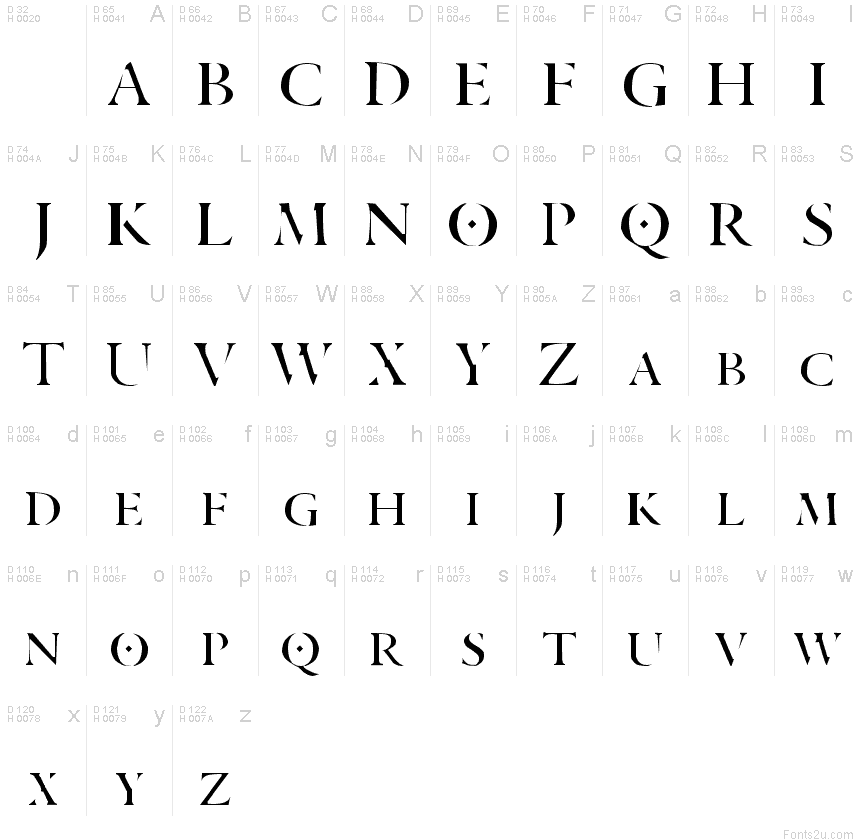
Aranea من rzy/SDFonts هو خط مزخرف بزوائد (serif) يضفي طابعاً مظلماً ومسرحياً. حروفه طويلة وأنيقة تنتهي برؤوس حادة كالإبر، وكأن ضربات القلم قد رُسمت بريشة حادة على ورق نقي. التباعد يبدو متقارباً ومقصوداً، مما يمنح الكلمات توتراً منسوجاً يشبه خيوط العنكبوت، وهو أمر يناسب كل ما هو غامض أو سحري أو خطر بعض الشيء.
باستخدام Aranea، تكتسب العناوين على الفور دراما قوطية أشبه بالقصص الخيالية يصعب تجاهلها. يتألق هذا الخط المجاني على أغلفة كتب الفانتازيا، ومجلات العالم الخفي (zines)، وشعارات الفرق الموسيقية، وملصقات الرعب، وتغليف أوراق التاروت، وبطاقات العناوين ذات الطابع الخاص. جرب دمج Aranea مع خط حديث وبسيط بلا زوائد (sans serif) في الأحجام الصغيرة للحفاظ على قابلية القراءة، مع ترك الخط الأساسي ليعبر عن كل الإثارة والزخرفة.